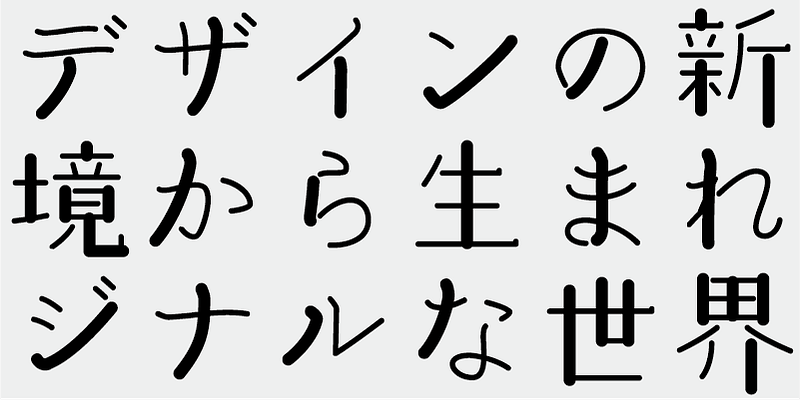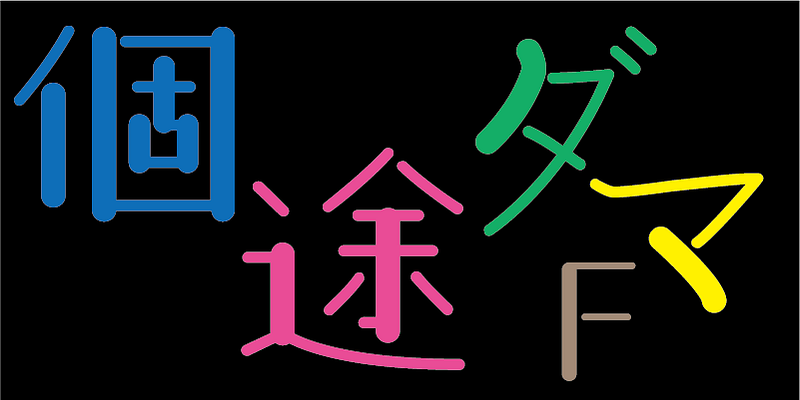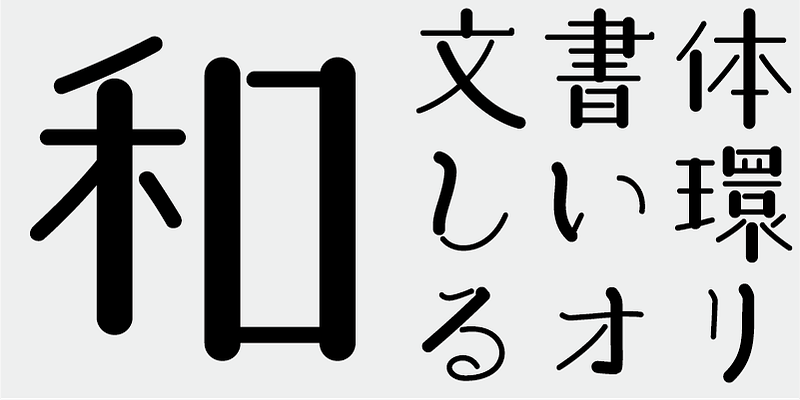
Diese Variante F basiert auf der Struktur von Kotodama R, wobei einige Striche stärker sind und so einzigartige visuelle Effekte entstehen.
Diese Schrift umfasst 1.000 wichtige Kanji-Zeichen, die aus einer von Zeitungen, Verlagen und Forschungsinstituten für Linguistik erstellten Tabelle der häufigsten Zeichen ausgewählt wurden, plus 206 Kana-Zeichen und Interpunktion.
In der heutigen japanischen Schriftproduktion gelten die 7.000 Zeichen des JIS-Standards als unabdingbar. Aber brauchen alle Schriften wirklich 7.000 Zeichen? Im Zeitalter des Fotosatzes wurden weit weniger Zeichen benötigt. FONT1000, eine Gruppe unabhängiger Schriftdesigner, ging von dieser einfachen Frage aus. Wir haben die mindestens 1.000 (ideografischen) Kanji-Zeichen ausgewählt, die für den Satz in Japanisch erforderlich sind, und aktiv Schriften und Schriftbilder dafür entworfen. Dieser 1000-Kanji-Zeichensatz wurde unter Verwendung von Zeichenhäufigkeitsdaten ausgewählt, die u. a. von Zeitungsunternehmen, Verlagen und Sprachforschungsinstituten zusammengestellt wurden, und enthält auch Kana-Silbenzeichen und Satzzeichen. FONT1000 begann 2001 mit 25 Designern und 25 Schriften. Heute haben wir 130 Schriften und sind auf fast 40 Mitglieder angewachsen, sodass wir an Schriften mit mehr Zeichen arbeiten können.